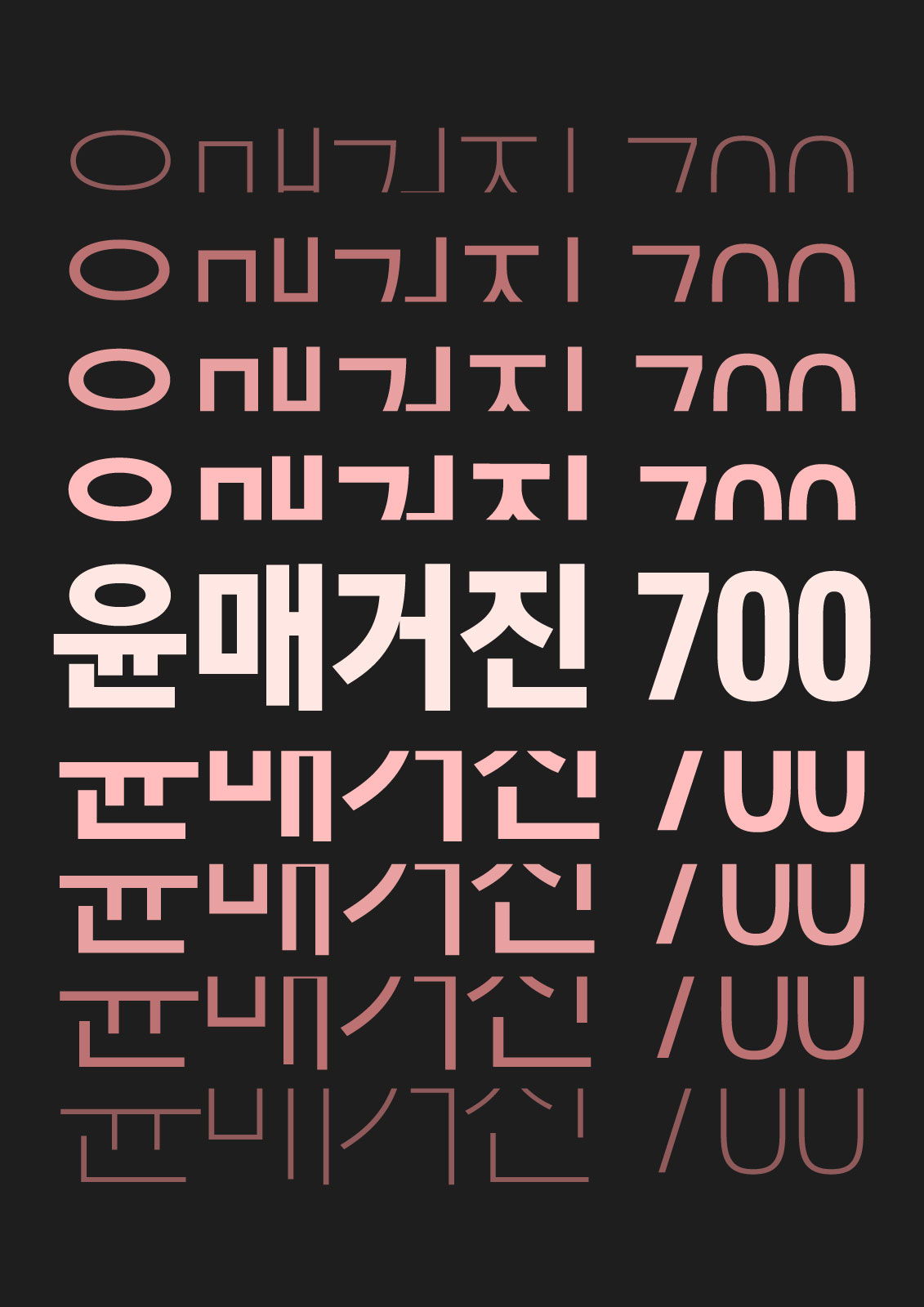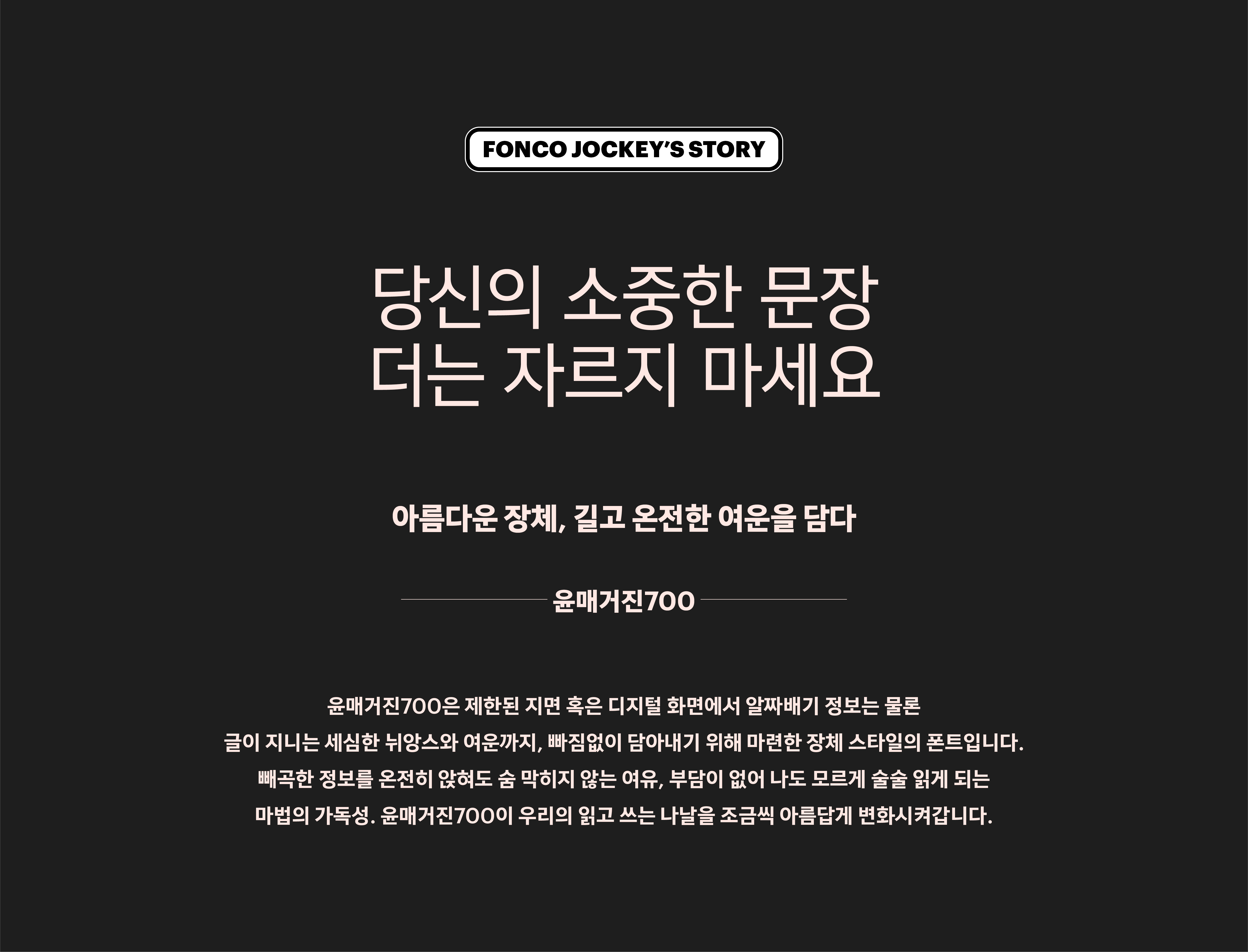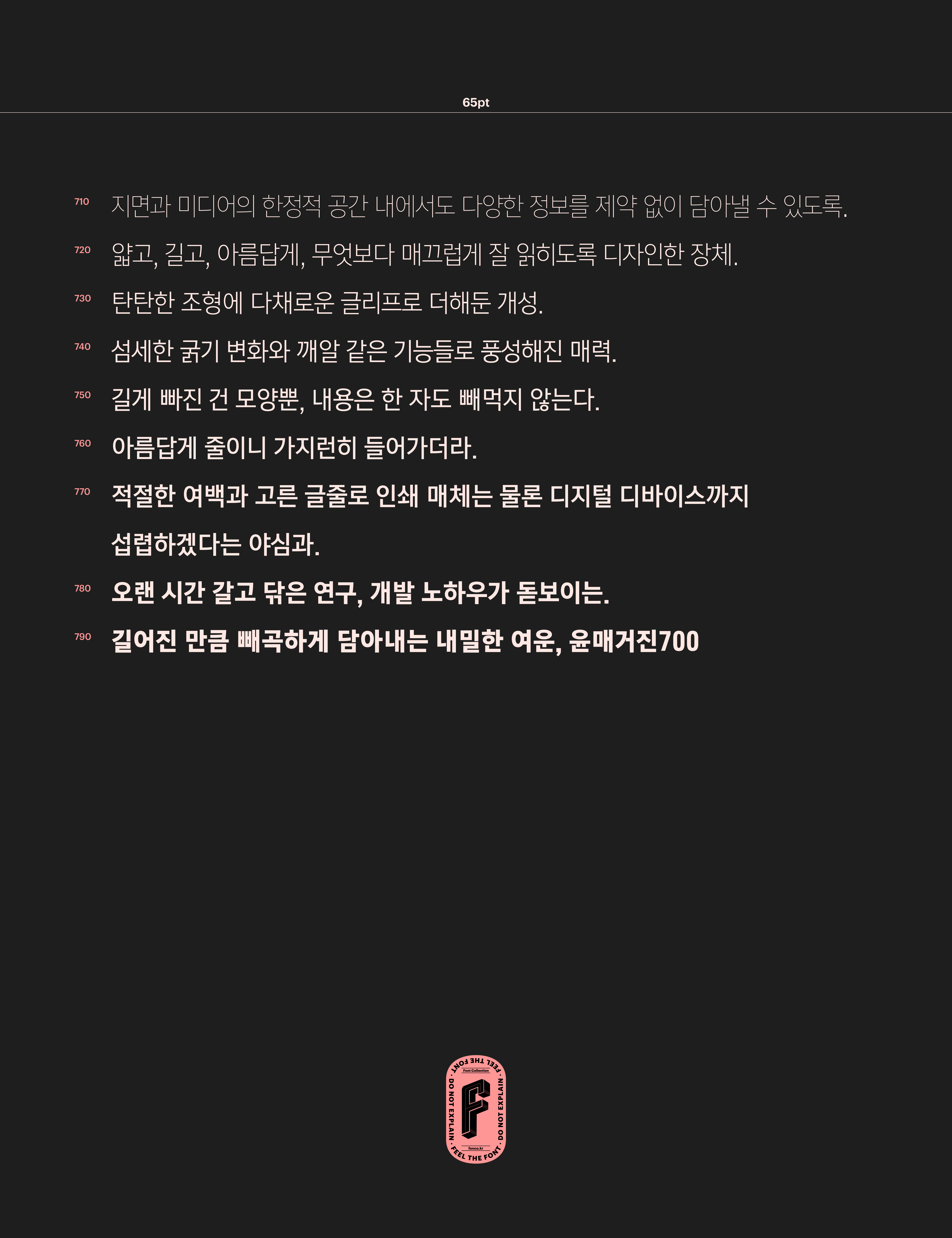
“저, 죄송한데 원고 길이를 조금만 줄여주실 수 있을까요?” 요청해본 경험이 있는 디자이너들, 모두모두 모여라! 윤매거진700은 제한된 지면 혹은 디지털 화면에 알짜배기 정보는 물론 글이 지니는 세심한 뉘앙스까지, 빠짐없이 담아내기 위해 마련한 장체 스타일의 폰트입니다. 빼곡한 정보를 온전히 담아도 숨 막히지 않는 여유. 윤매거진700과 함께 느껴보세요.
Yoon 윤매거진700